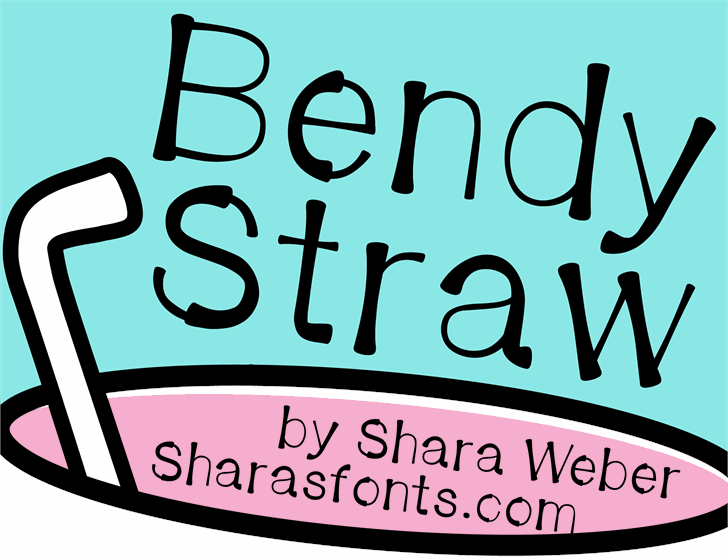
A BendyStraw Font é uma fonte display criada pelo designer Hamilton que oferece uma experiência visual única e divertida. Com linhas curvas e flexíveis, essa fonte destaca-se entre as demais, adicionando um toque de personalidade e irreverência a qualquer projeto onde ela for usada. Seu design fluido e contínuo cria uma sensação de movimento, tornando-a perfeita para aplicar em elementos que exijam atenção especial, como títulos ou headlines. Para quem busca algo diferente e criativo, esta fonte é a escolha ideal. A BlendyStraw Font é perfeitamente adaptável à maioria dos estilos de design moderno, tornando-a uma fonte versátil para projetos em tela cheia e redes sociais.